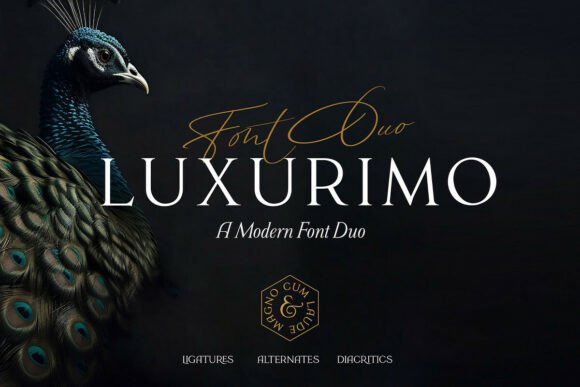
Luxurimo
Nếu bạn đang tìm kiếm các tài nguyên chất lượng cao như Luxurimo, gói cao cấp này là một lựa chọn tuyệt vời cho các dự án sáng tạo của bạn.
Được chế tác với độ chính xác cao, Luxurimo cung cấp các vector sạch, kiểu chữ mượt mà và giấy phép thương mại để bạn yên tâm.
Cho dù bạn đang tạo sản phẩm POD (In theo yêu cầu), thiệp mời đám cưới hay đồ họa mạng xã hội, Luxurimo đều là một sự lựa chọn lý tưởng.